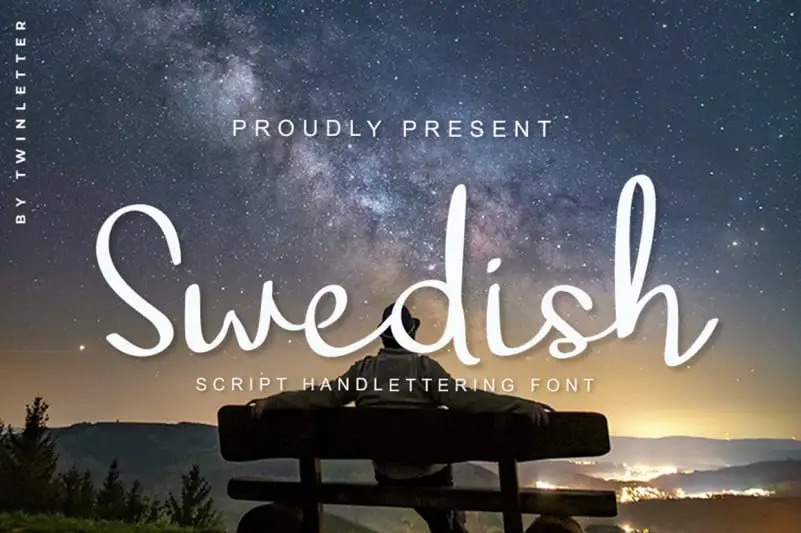
Swedish Script Font – Download Grátis
A Swedish Script Font é uma peça única para qualquer projeto criativo que você possa imaginar. Embora seja intitulada ‘Swedish’, ela não precisa ser apenas associada à língua ou cultura sueca, mas sim ao seu equilíbrio entre fofura e autenticidade. Este belo tipo de escrita manuscrita é perfeito para dar um toque chamativo a qualquer logomarca, identidade visual, projeto de mídias sociais ou até mesmo sua próxima peça DIY. Com características quirkicamente divertidas, essa fonte se destaca do resto da arrecadação. Ela captura o espírito criativo e autêntico que você busca em seu trabalho, seja ele um design de logomarca inovador ou uma etiqueta para sua próxima obra de arte caseira. Não importa qual caminho escolha para aplicar essa fonte, ela certamente ajudará a tornar seu projeto único, marcante e irresistivelmente chamativo no meio do resto da arrecadação.